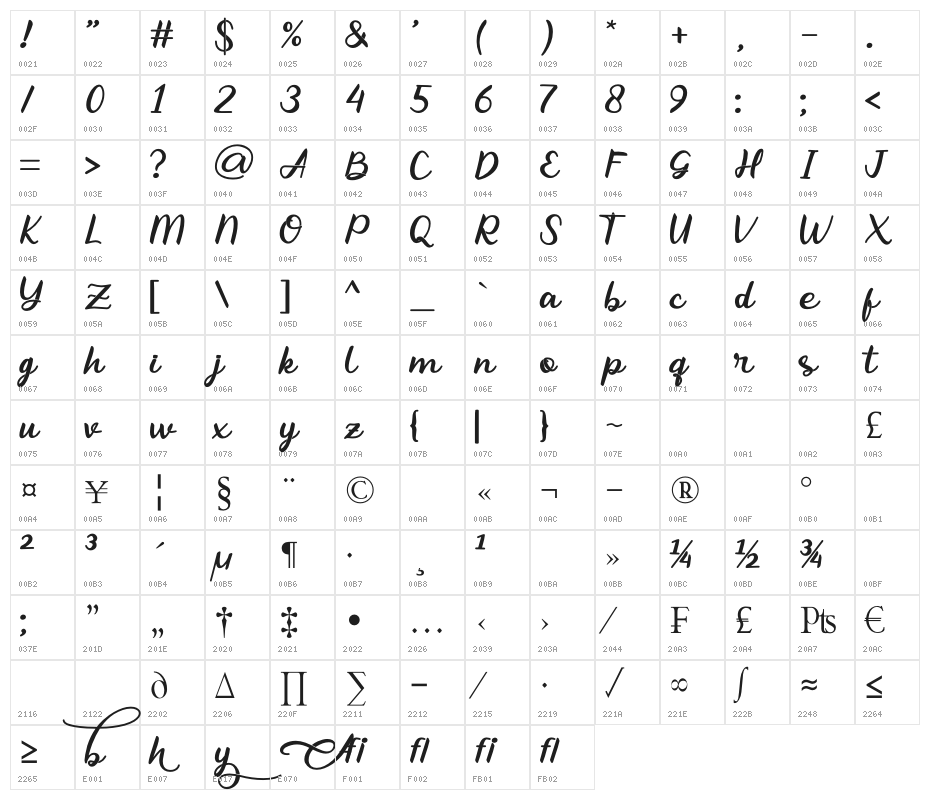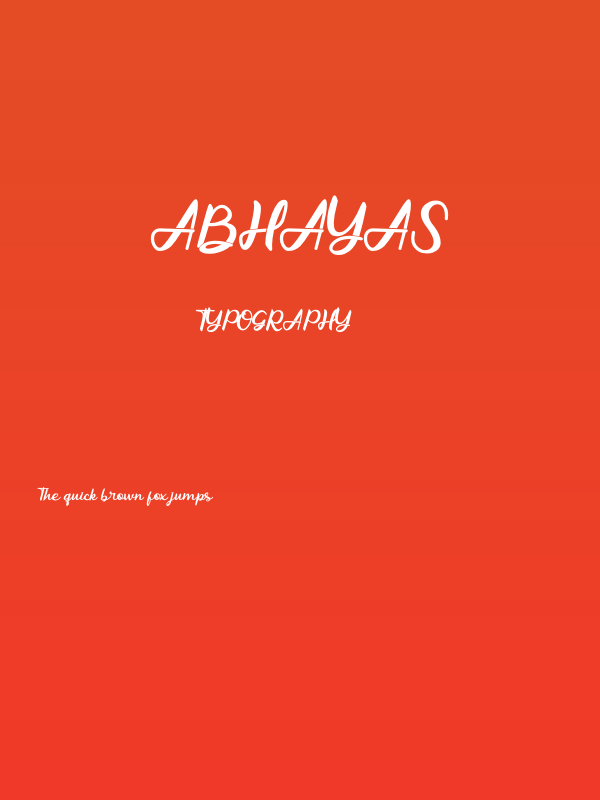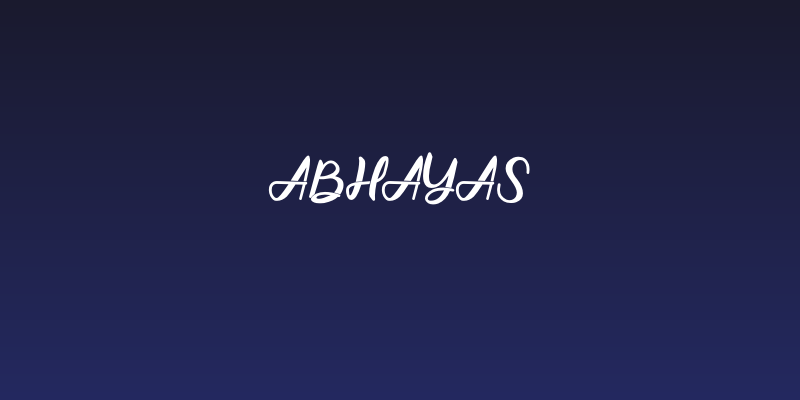
Abhayas Font
| Stile generale | Elegant, Handwritten |
| Caso d'uso | Logos, Invitations, Decorative text |
| Progetti proposti | Ideal for wedding invitations, greeting cards, personal branding, and elegant packaging designs. |